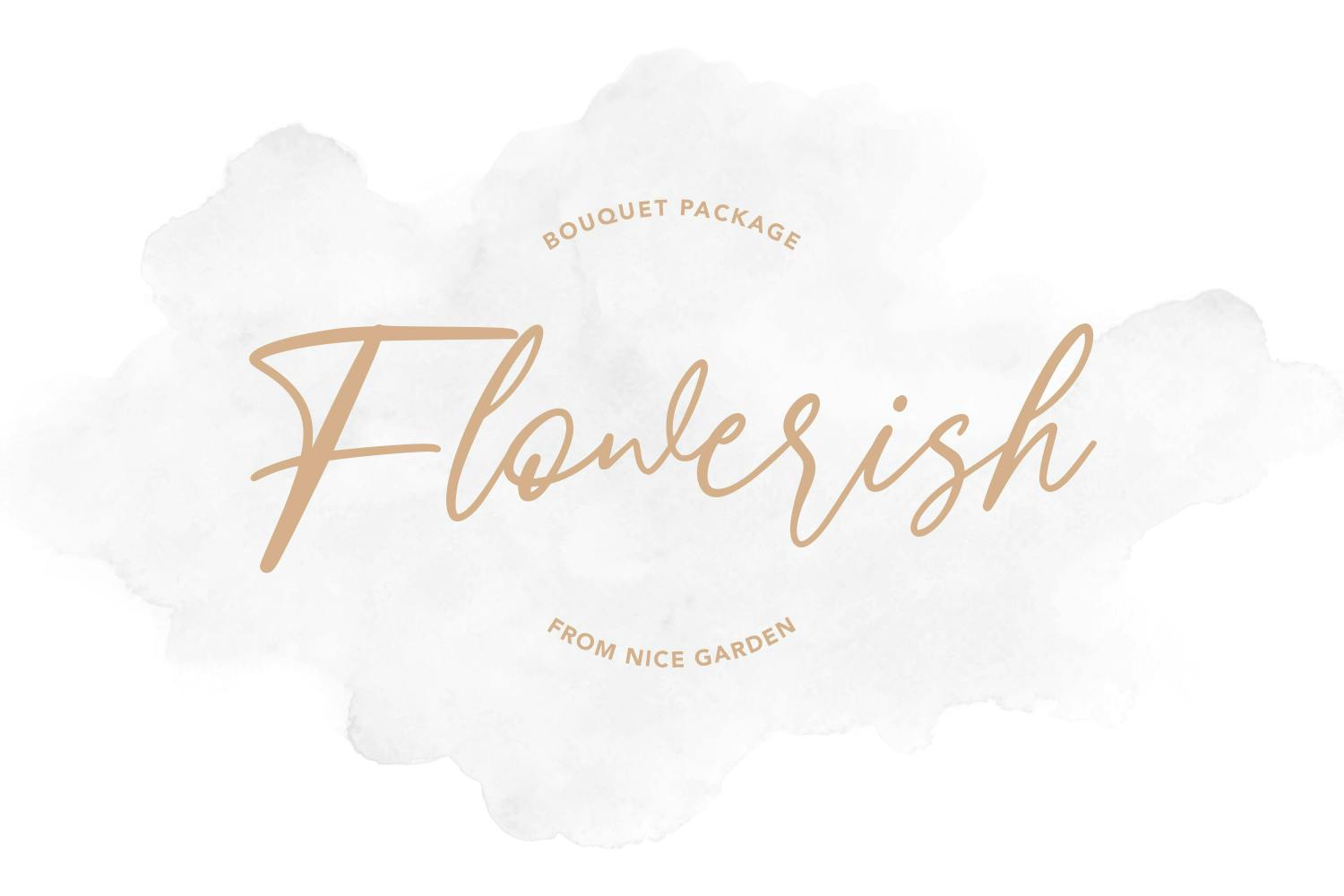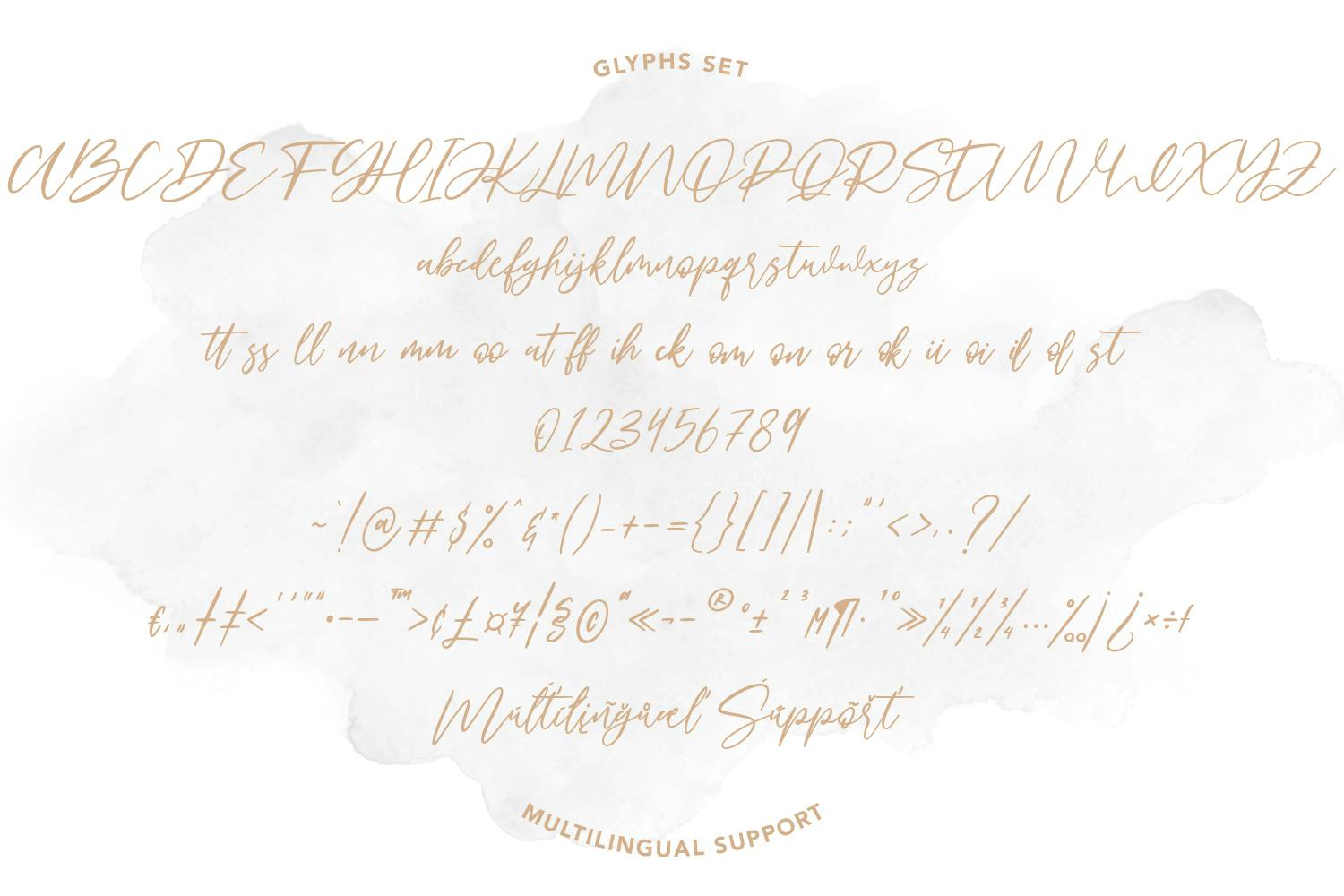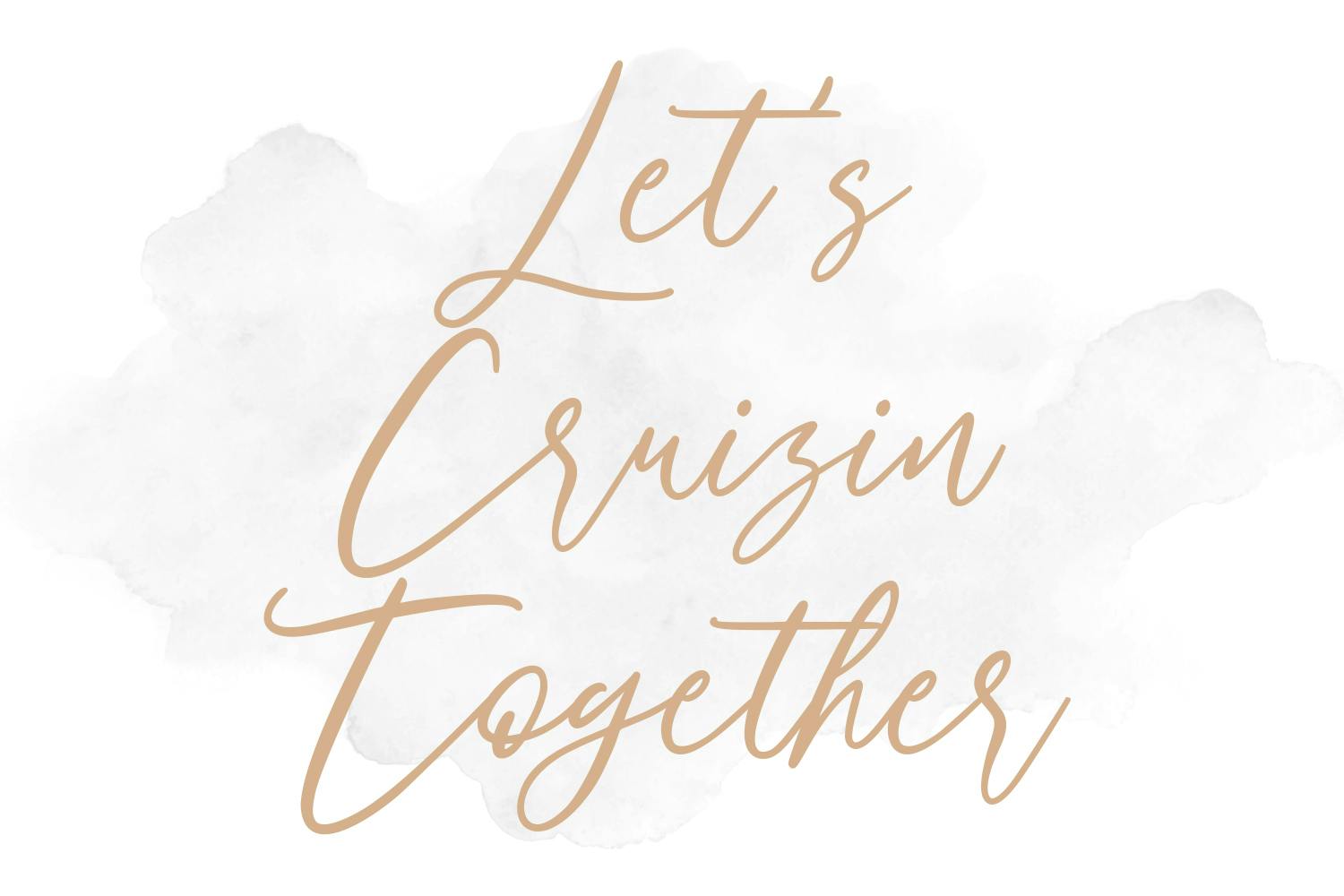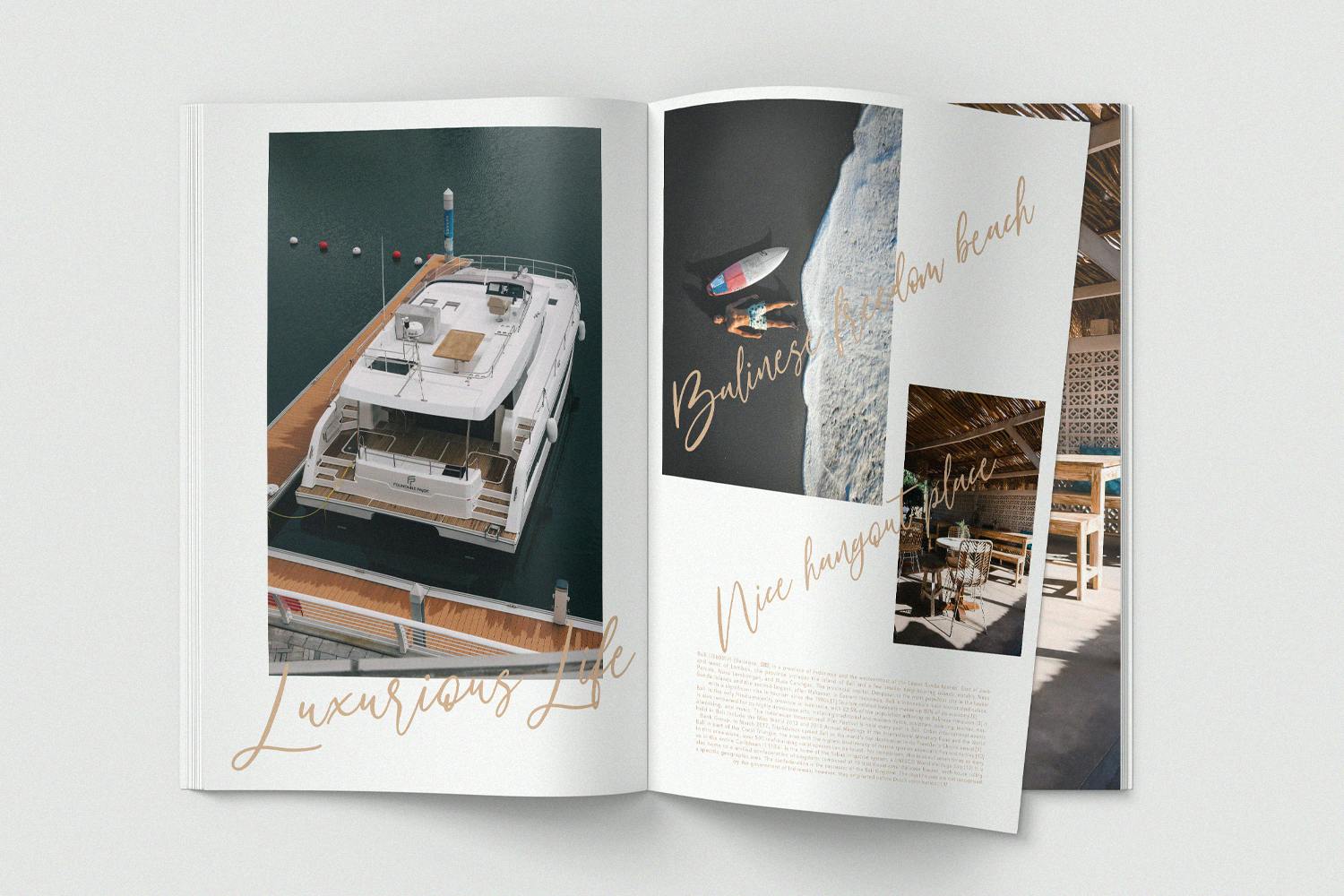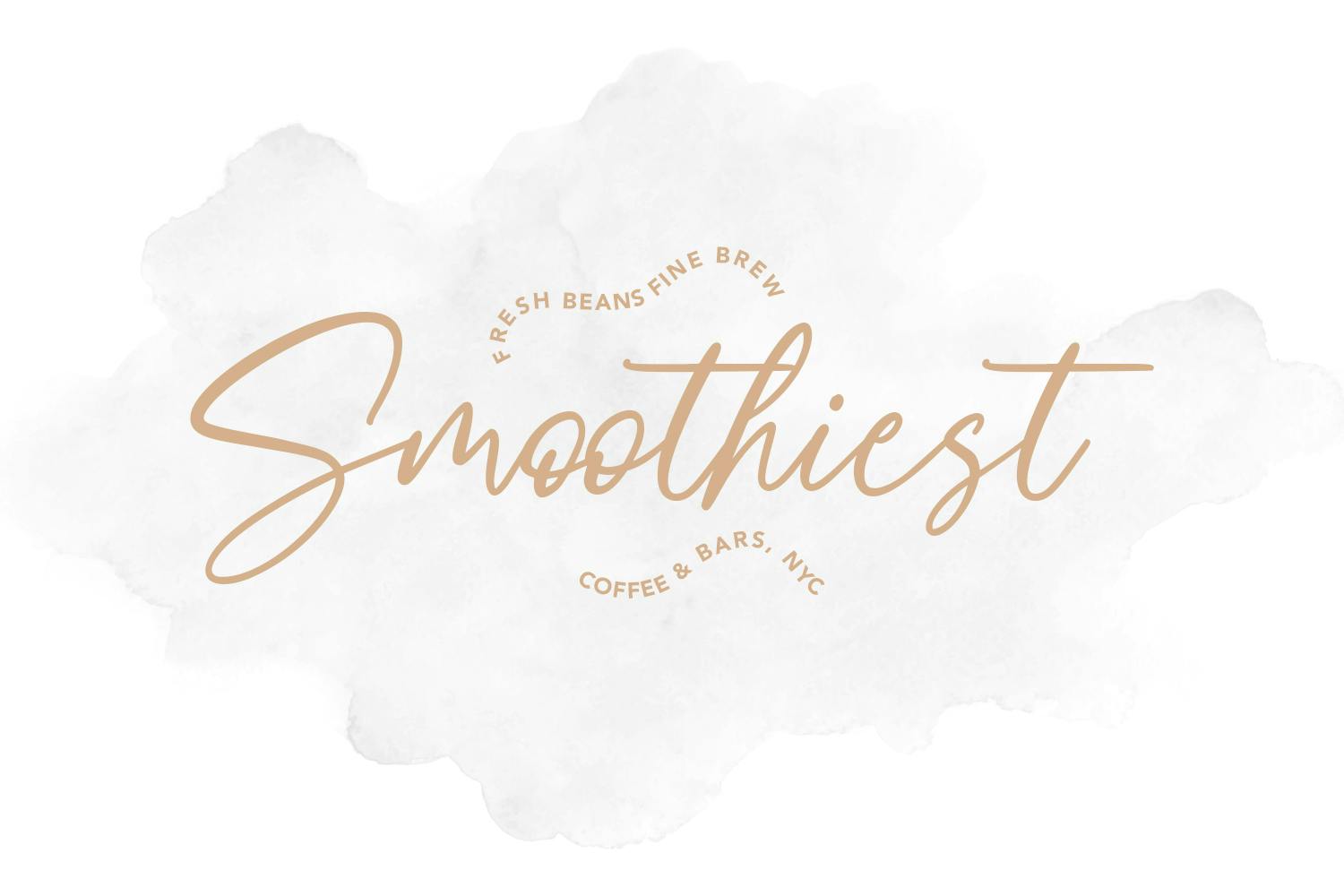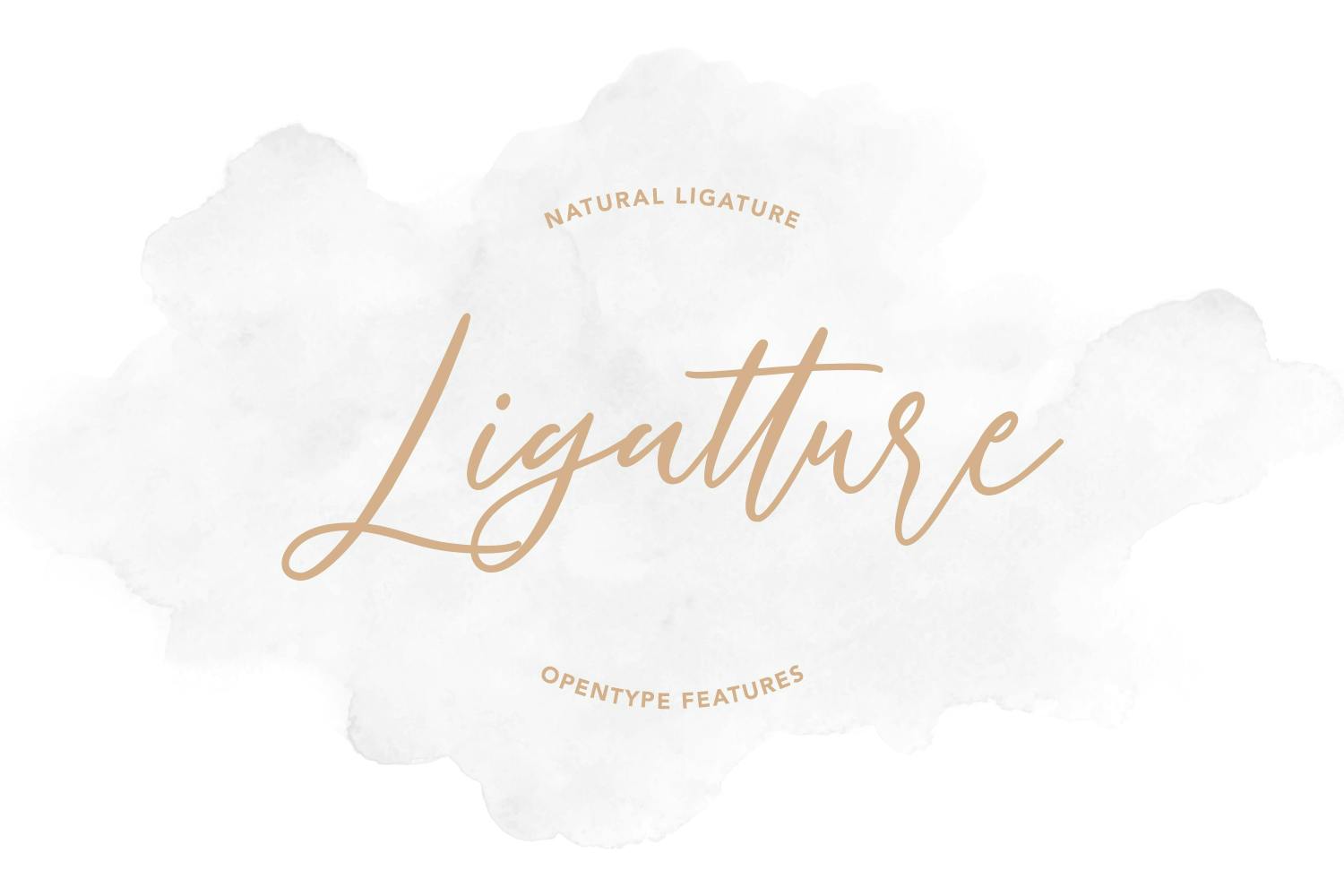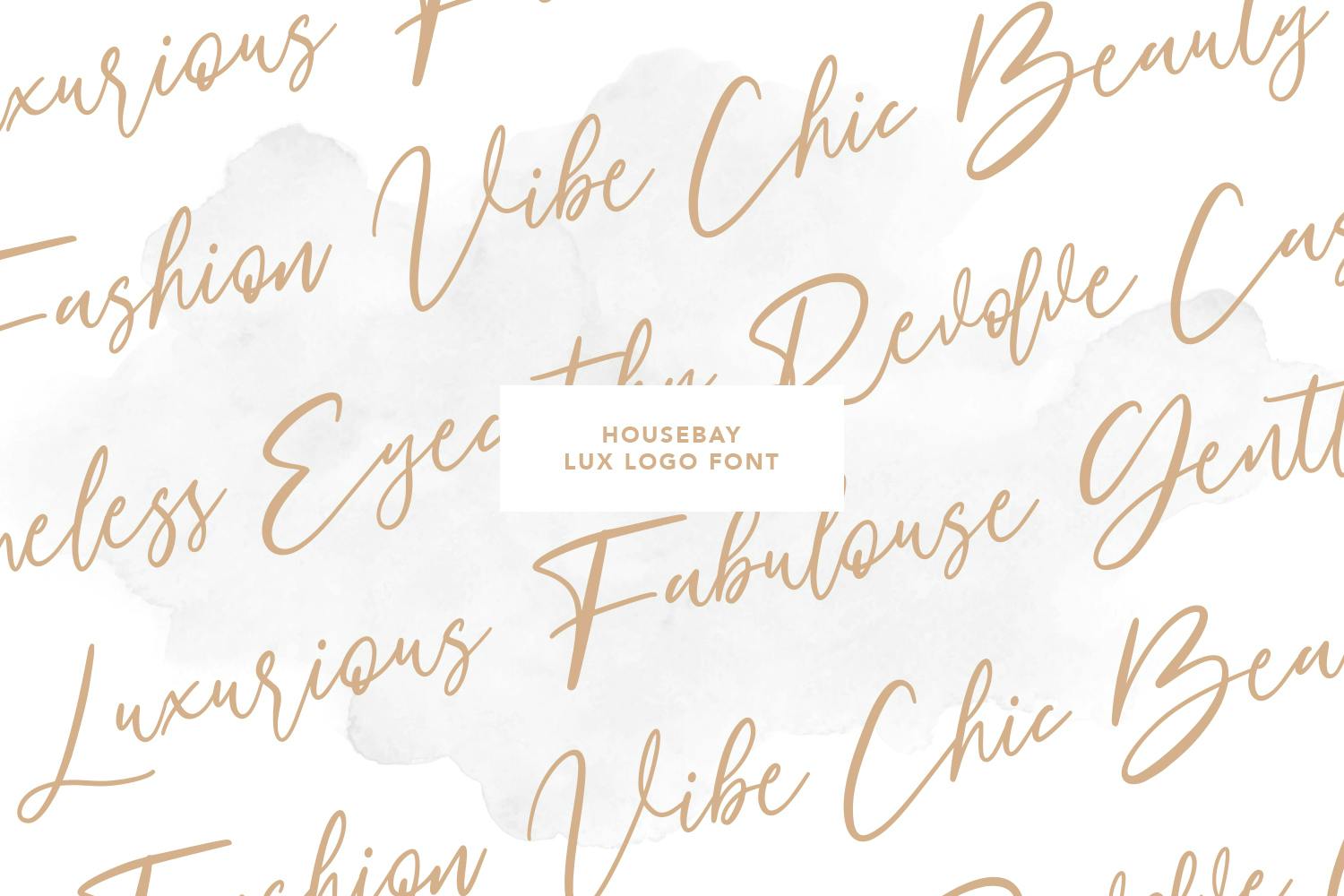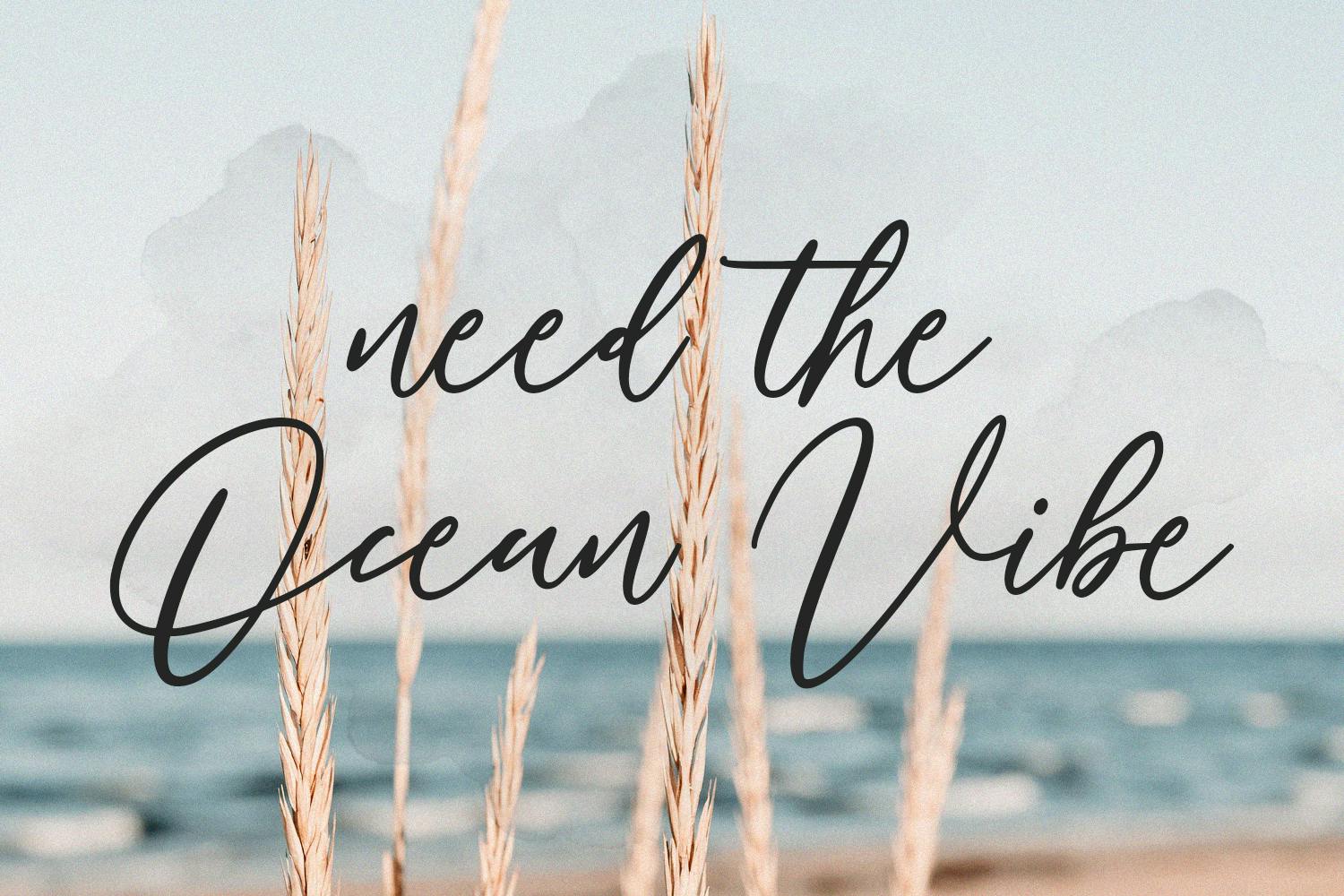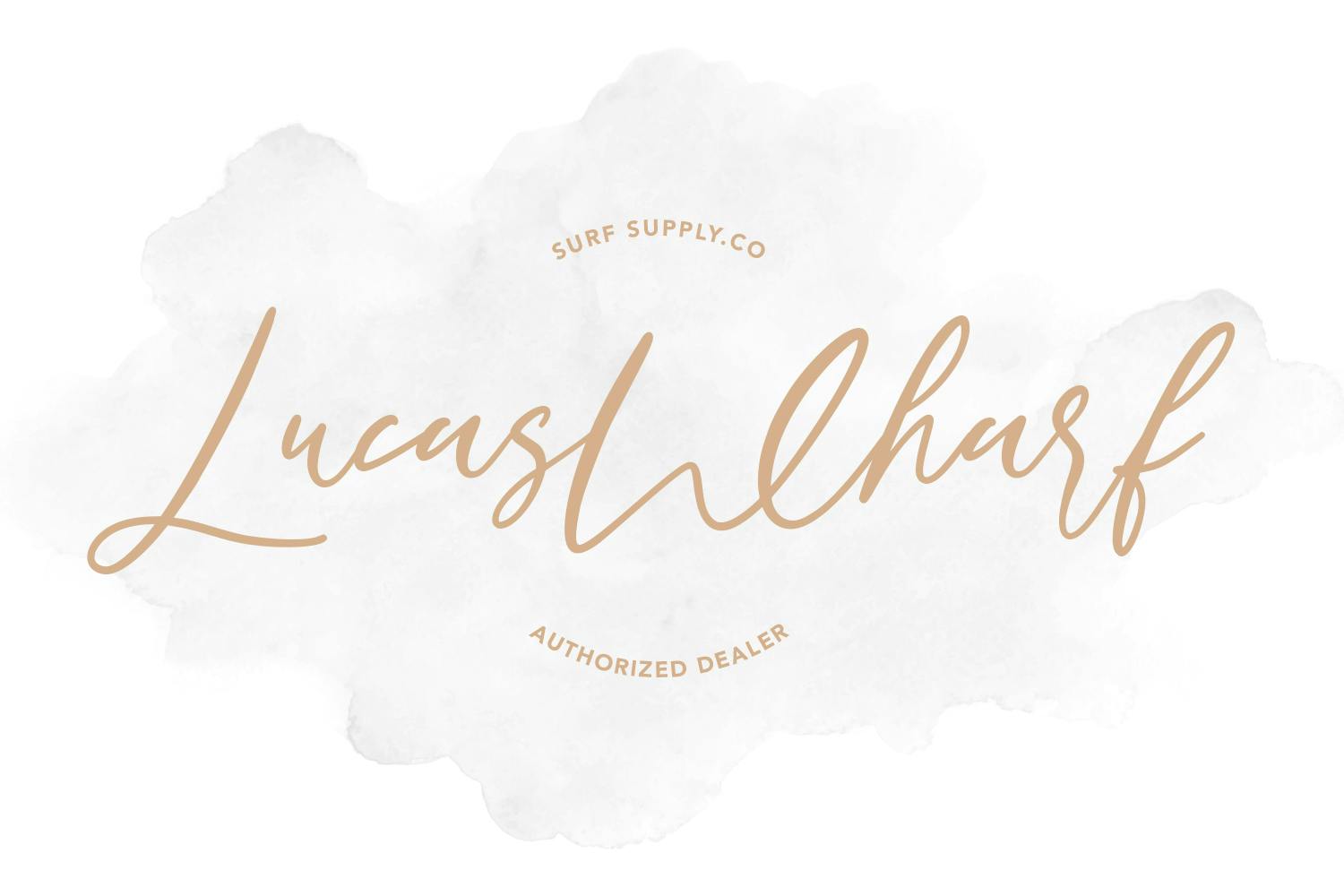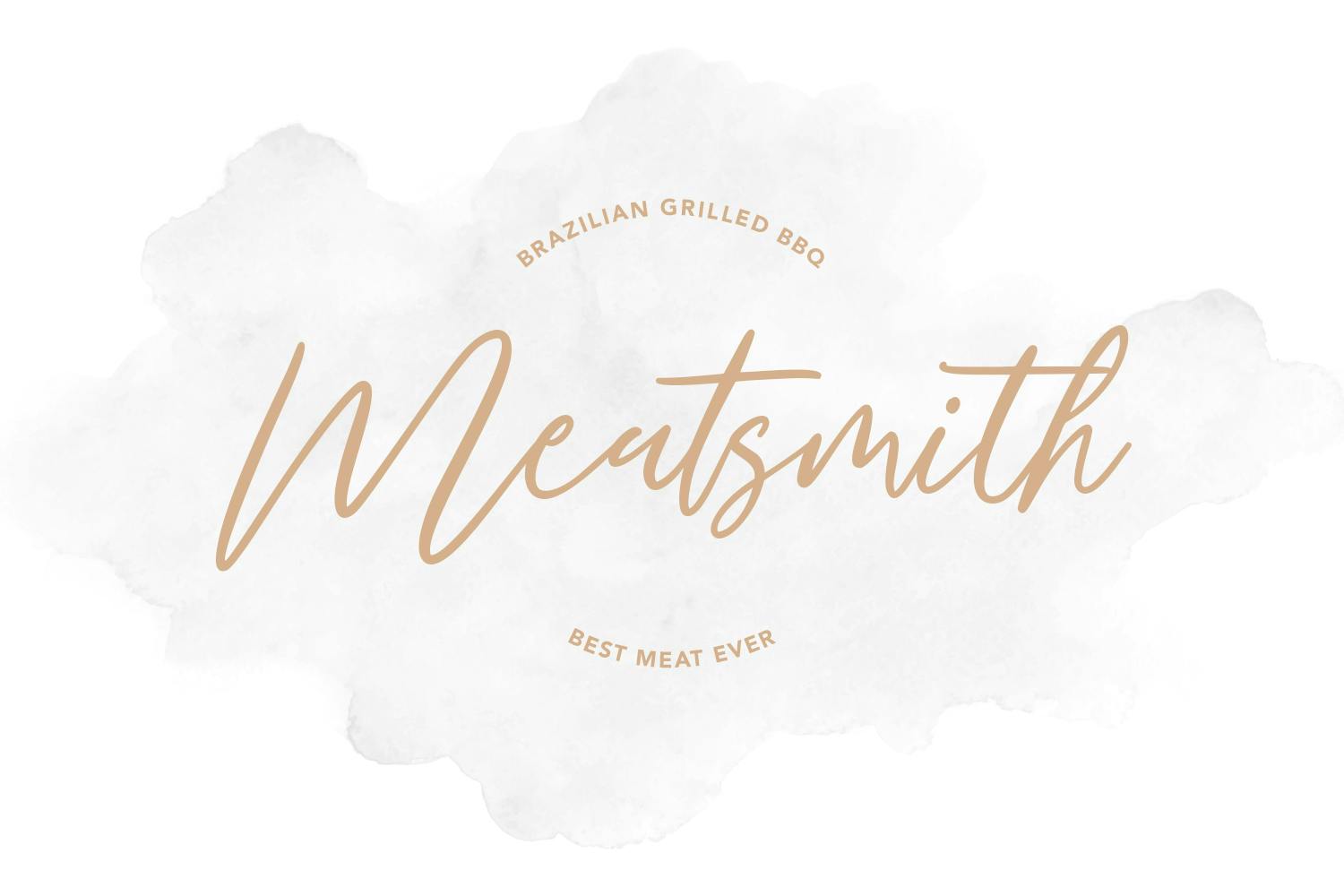
فونت اسکریپت لوگو هاوس بی
به طرحهای شما حس دستساز و اصیل میبخشد. فونت HouseBay Logo Script بهطور کامل برای طراحی لوگو، لوازمالتحریر، برندینگ، نقلقولهای تایپوگرافی، جلد مجله یا کتاب، هدر وبسایت، لباس، برندینگ، طراحی بستهبندی، رستوران و بسیاری دیگر مناسب است.